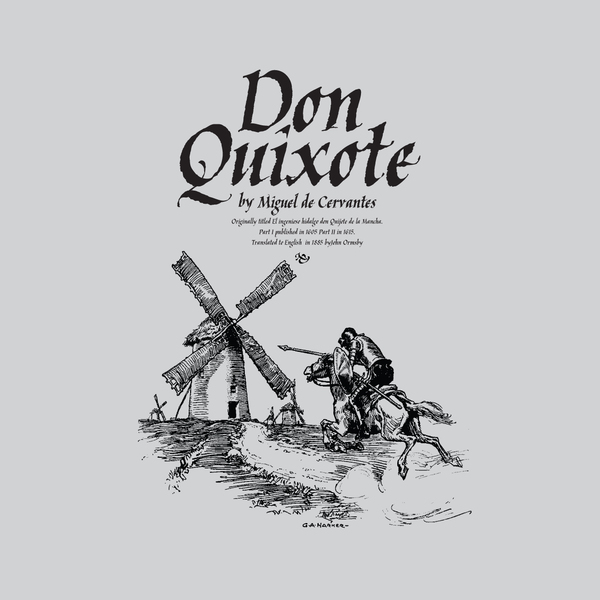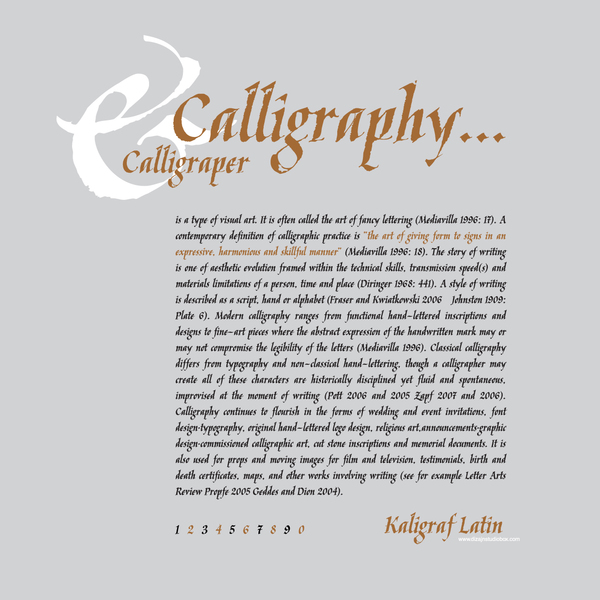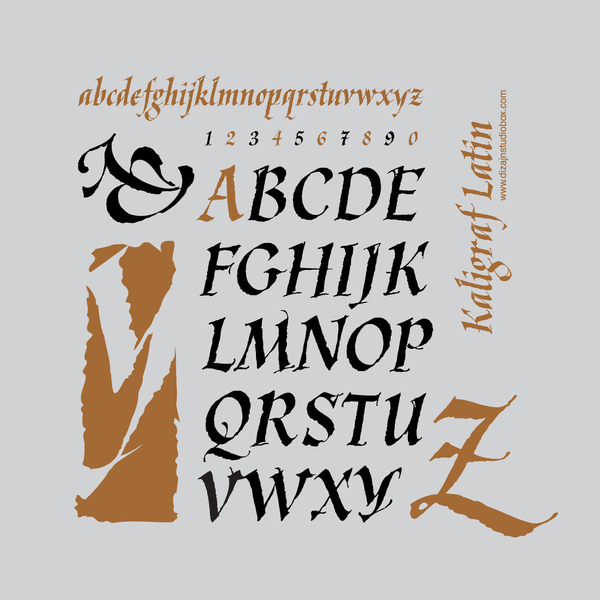
Kaligraf 1.0
Dekorativer Kalligrafie-Font von Lazar Dimitrijević mit kompletter westeuropäischer Belegung. Zusätzlich im Download-Paket ist eine kyrillische Version (jedoch nicht Unicode-kodiert).
Lazar Dimitrijević
Eine der schönsten und leserlichsten kaligrafischen Schriften die ich bisher gefunden habe. Sehr gut leserlich auch bei Schriftgrößen ab 9 - 11. Ich werde sie besonders für Lyriks, Gedichte (z.T. mittelalterlich) und Geschichten (angelehnt an der älteren Zeit vom Mittelalter bis zur Barockzeit). Für mich die absolute Nr. 1 unter den kaligrafischen Schriften die ich in den letzten 10 Jahren gefunden habe. 👍
Trotz oder gerade wegen des "schon-mal-gesehen"-Effekts sehr ansprechender Font!